ฟอนต์ผิด ชีวิตเปลี่ยน! คู่มือเลือกฟอนต์สำหรับแบรนด์ SME
ในโลกของการสร้างแบรนด์สำหรับธุรกิจขนาดกลางและขนาดย่อม (SME) ทุกองค์ประกอบมีความสำคัญ ตั้งแต่สี โลโก้ ไปจนถึง “ฟอนต์” หรือรูปแบบตัวอักษรที่ใช้ หลายคนอาจมองข้ามความสำคัญของฟอนต์ แต่ในความเป็นจริงแล้ว ฟอนต์คือหนึ่งในเครื่องมือสื่อสารที่ทรงพลังที่สุดที่สามารถกำหนดการรับรู้และสร้างความสัมพันธ์กับลูกค้าได้
ประเด็นสำคัญของการเลือกฟอนต์สำหรับธุรกิจ
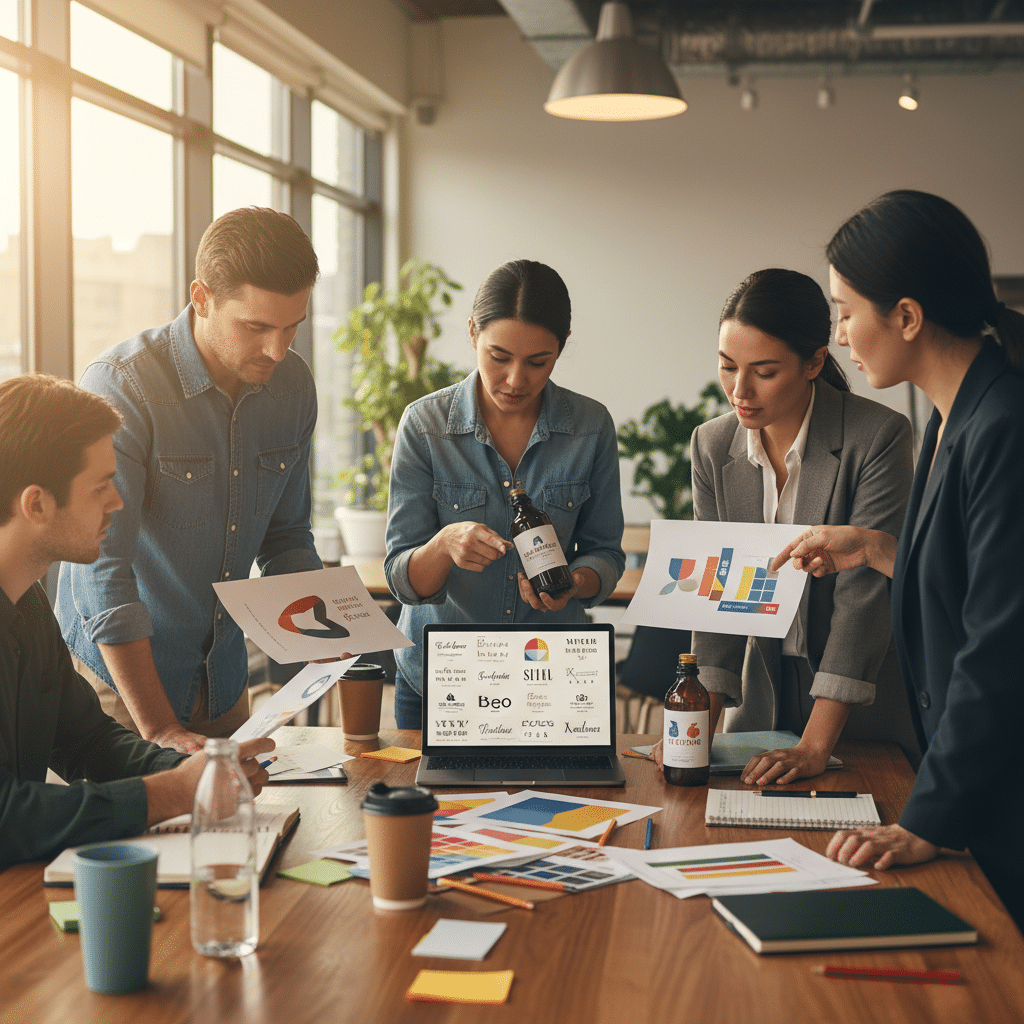
- ฟอนต์คือเสียงของแบรนด์: รูปแบบตัวอักษรที่เลือกใช้ต้องสอดคล้องกับบุคลิก ค่านิยม และข้อความที่แบรนด์ต้องการสื่อสารไปยังกลุ่มเป้าหมาย เพื่อสร้างภาพลักษณ์ที่ชัดเจนและเป็นที่จดจำ
- ความชัดเจนต้องมาก่อนเสมอ: ไม่ว่าฟอนต์จะสวยงามหรือมีเอกลักษณ์เพียงใด หากอ่านยากหรือไม่ชัดเจนในขนาดต่างๆ ก็อาจสร้างประสบการณ์ที่ไม่ดีและลดทอนความน่าเชื่อถือของแบรนด์ได้
- จิตวิทยาและการจับคู่สร้างความแตกต่าง: การทำความเข้าใจจิตวิทยาเบื้องหลังฟอนต์แต่ละประเภท และเทคนิคการจับคู่ฟอนต์ (Font Pairing) ที่ลงตัว จะช่วยสร้างลำดับชั้นของข้อมูลและเสริมสร้างเอกลักษณ์ของแบรนด์ให้โดดเด่น
ทำไมฟอนต์ถึงมีความสำคัญต่อแบรนด์ SME
เพราะเหตุใด ฟอนต์ผิด ชีวิตเปลี่ยน! คู่มือเลือกฟอนต์สำหรับแบรนด์ SME จึงเป็นหัวข้อที่ผู้ประกอบการไม่ควรมองข้าม? คำตอบนั้นเรียบง่ายแต่ลึกซึ้ง: ฟอนต์คือ “เสียงที่มองเห็นได้” ของแบรนด์ (Visual Voice) ก่อนที่ลูกค้าจะได้อ่านข้อความ พวกเขาจะ “รู้สึก” ถึงบุคลิกของแบรนด์ผ่านรูปแบบตัวอักษรเสียก่อน ฟอนต์ที่ดูสนุกสนานและเป็นกันเองอาจไม่เหมาะกับสำนักงานกฎหมายที่ต้องการความน่าเชื่อถือ ในทางกลับกัน ฟอนต์ที่ดูเคร่งขรึมและเป็นทางการก็อาจทำให้แบรนด์ของเล่นดูไม่น่าสนใจสำหรับเด็ก
สำหรับเจ้าของธุรกิจ SME นักการตลาด หรือนักออกแบบที่กำลังอยู่ในช่วงสร้างแบรนด์ ปรับปรุงภาพลักษณ์ หรือออกแบบสื่อต่างๆ การเลือกฟอนต์ที่ถูกต้องจึงเป็นขั้นตอนเชิงกลยุทธ์ที่ส่งผลโดยตรงต่อการรับรู้ของลูกค้า สร้างความไว้วางใจ และทำให้แบรนด์แตกต่างจากคู่แข่งในตลาด การลงทุนเวลาเพื่อทำความเข้าใจและเลือกฟอนต์ที่เหมาะสมจึงเป็นการลงทุนที่คุ้มค่าในระยะยาว
หลักการพื้นฐานในการเลือกฟอนต์ให้ตรงใจแบรนด์
การเลือกฟอนต์ไม่ใช่เรื่องของความชอบส่วนตัว แต่เป็นกระบวนการที่ต้องพิจารณาจากหลักการพื้นฐาน 4 ประการ เพื่อให้แน่ใจว่าฟอนต์ที่เลือกนั้นทำงานได้อย่างมีประสิทธิภาพและสนับสนุนเป้าหมายของแบรนด์
สะท้อนตัวตนและบุคลิกภาพของแบรนด์
ก่อนจะเลือกฟอนต์ใดๆ ต้องตอบคำถามให้ได้ก่อนว่า “แบรนด์มีบุคลิกอย่างไร” เป็นแบรนด์ที่ทันสมัย มินิมอล หรือเป็นแบรนด์ที่เน้นความดั้งเดิมและน่าเชื่อถือ? การกำหนดบุคลิกของแบรนด์ให้ชัดเจนจะช่วยจำกัดตัวเลือกของฟอนต์ให้แคบลง
- แบรนด์ทันสมัยและเทคโนโลยี: มักนิยมใช้ฟอนต์ในกลุ่ม Sans Serif ที่มีเส้นสายเรียบง่าย สะอาดตา สื่อถึงความตรงไปตรงมาและเข้าถึงง่าย
- แบรนด์ที่เน้นความน่าเชื่อถือและประเพณี: มักเลือกใช้ฟอนต์กลุ่ม Serif ที่มี “เชิง” หรือขีดเล็กๆ ที่ปลายตัวอักษร ซึ่งให้ความรู้สึกมั่นคง เป็นทางการ และคลาสสิก
- แบรนด์ที่เน้นความหรูหราหรือความคิดสร้างสรรค์: อาจเลือกใช้ฟอนต์กลุ่ม Script หรือฟอนต์ลายมือ ที่ให้ความรู้สึกพิเศษ เป็นกันเอง และมีศิลปะ
ความชัดเจนและการอ่านง่าย
ความสวยงามจะไร้ความหมายหากผู้รับสารไม่สามารถอ่านข้อความได้อย่างสะดวกสบาย ความชัดเจน (Legibility) คือความสามารถในการแยกแยะตัวอักษรแต่ละตัวออกจากกัน ในขณะที่การอ่านง่าย (Readability) คือความสะดวกในการอ่านข้อความยาวๆ ฟอนต์ที่ดีต้องมีคุณสมบัติทั้งสองอย่าง โดยเฉพาะเมื่อนำไปใช้ในสื่อที่แตกต่างกัน
ข้อควรพิจารณาคือ ฟอนต์ที่ออกแบบมาสำหรับพาดหัวข่าวอาจไม่เหมาะกับเนื้อหาบทความยาวๆ และฟอนต์ที่ดูดีบนหน้าจอคอมพิวเตอร์อาจอ่านยากเมื่อพิมพ์ลงบนฉลากสินค้าขนาดเล็ก
การเข้าถึงกลุ่มเป้าหมาย
ฟอนต์ที่เลือกต้องสอดคล้องกับความคาดหวังและความคุ้นเคยของกลุ่มเป้าหมาย การเลือกฟอนต์ที่ซับซ้อนเกินไปสำหรับผลิตภัณฑ์ที่มุ่งเป้าไปที่ผู้สูงอายุอาจทำให้การสื่อสารล้มเหลว ในขณะที่การใช้ฟอนต์ที่เป็นทางการเกินไปสำหรับแบรนด์วัยรุ่นอาจทำให้แบรนด์ดูน่าเบื่อและไม่เข้าถึง การวิเคราะห์ประชากรศาสตร์และความชอบของลูกค้าจึงเป็นส่วนสำคัญในการเลือกฟอนต์ที่ “ใช่”
สร้างความแตกต่างและน่าจดจำ
ในตลาดที่มีการแข่งขันสูง ฟอนต์สามารถเป็นเครื่องมือสร้างความแตกต่างที่มีประสิทธิภาพ การเลือกใช้ฟอนต์ที่ไม่เหมือนใครหรือมีการปรับแต่งเล็กน้อย (Customization) สำหรับโลโก้หรือแคมเปญการตลาด จะช่วยให้แบรนด์เป็นที่จดจำและโดดเด่นจากคู่แข่งได้ อย่างไรก็ตาม ความแตกต่างนี้ต้องไม่ลดทอนความชัดเจนในการอ่าน
จิตวิทยาของฟอนต์: ความรู้สึกที่ซ่อนอยู่ในตัวอักษร
ฟอนต์แต่ละประเภทมีพลังในการกระตุ้นอารมณ์และความรู้สึกที่แตกต่างกัน การทำความเข้าใจจิตวิทยาฟอนต์จะช่วยให้สามารถเลือกใช้ตัวอักษรเพื่อสื่อสารข้อความที่ต้องการได้อย่างแม่นยำยิ่งขึ้น
Serif: ความน่าเชื่อถือและประเพณีนิยม
ฟอนต์มีเชิง (Serif) เช่น Times New Roman, Garamond, หรือ Georgia มักให้ความรู้สึกถึงความมั่นคง ความเป็นทางการ ความน่าเชื่อถือ และความคลาสสิก ด้วยประวัติศาสตร์อันยาวนาน ฟอนต์ประเภทนี้จึงมักถูกใช้โดยสถาบันการเงิน สำนักพิมพ์หนังสือพิมพ์ บริษัทกฎหมาย หรือแบรนด์ที่ต้องการสร้างภาพลักษณ์ที่น่าเคารพและสืบทอดมายาวนาน